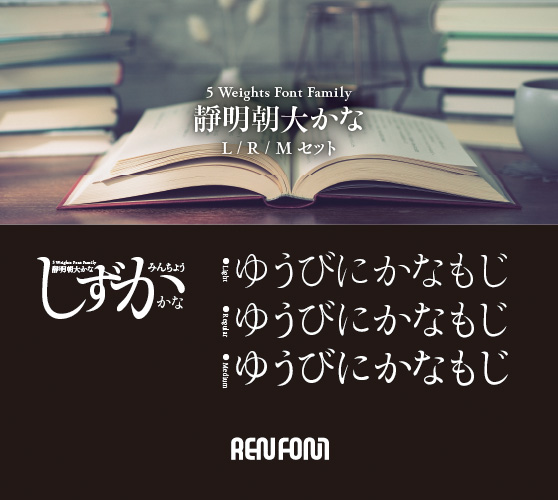
靜明朝大かな-テキスト用3ウェイトセット(L/R/M)
「小説などの長文を組んでもらいたい」とのコンセプトをもとに開発しました。靜明朝には「大かな」と「小かな」があり、このフォントは横組みに適した「大かな」です。横組みの長文に使ってみてください。落ち着いた、それでいながら訴求力のある紙面になるはずです。縦組み、横組みともプロポーショナル加工を加えました。また、ペアカーニングも緻密にほどこしてあります。テキスト用3ウェイトセット。